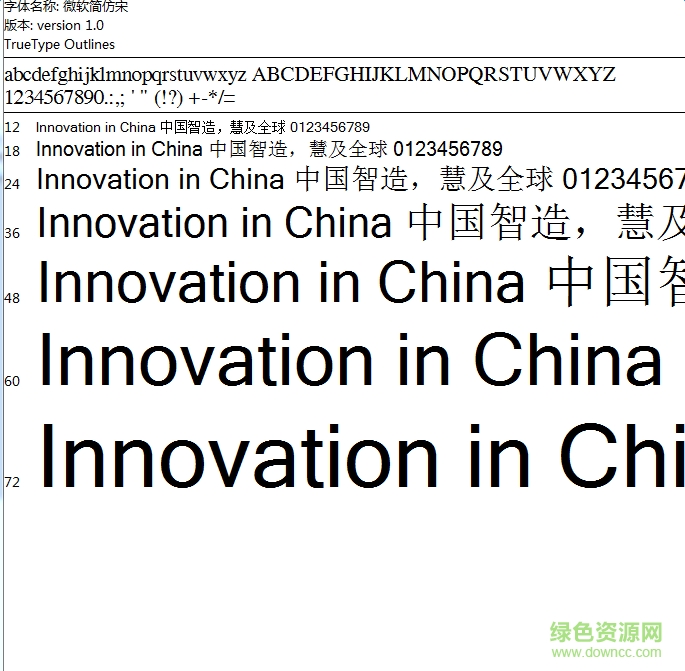
ctfangsongsf字體是一類(lèi)英文字體,字體線(xiàn)條清晰脫俗,整體效果十分優(yōu)美,在正式書(shū)法場(chǎng)合有著不錯(cuò)的應(yīng)用,更多好看字體盡在綠色資源網(wǎng)!
ctfangsongsf字體是一款用于印刷行業(yè)設(shè)計(jì)字體,被評(píng)為設(shè)計(jì)師最?lèi)?ài)的字體,ctfangsongsf風(fēng)格,簡(jiǎn)潔現(xiàn)代的線(xiàn)條,非常受到追捧。
ctfangsongsf即為微軟簡(jiǎn)仿宋!